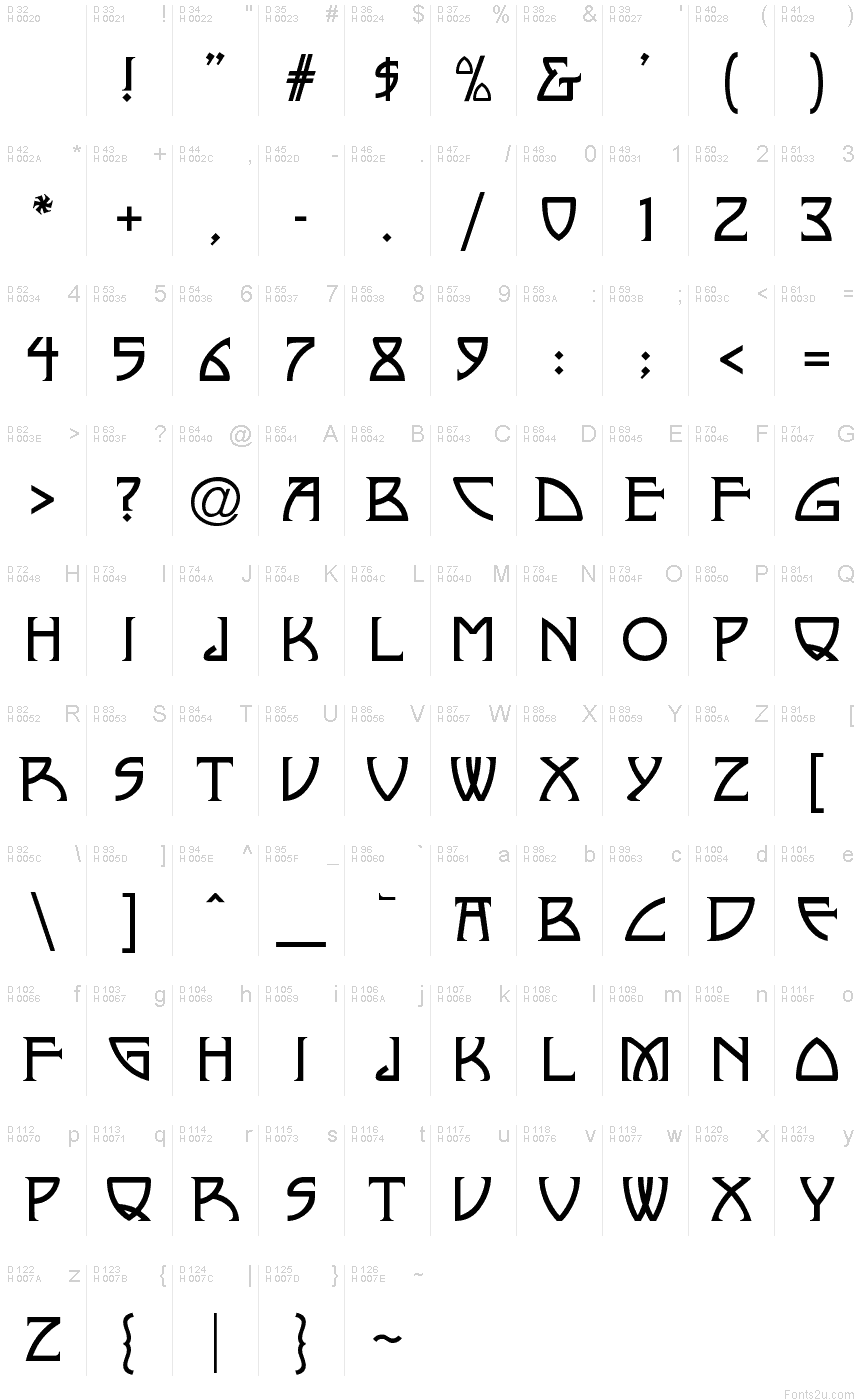
Nickley è il font display retro gratuito di Nick Curtis, con maiuscole che richiamano l'atmosfera dei poster Art Nouveau. L'alternanza di verticali slanciate, curve ampie e avvolgenti e piccoli dettagli affilati rende questo alfabeto elegante e leggermente eccentrico, evitando ogni rigidità formale.
È la scelta naturale per il branding vintage, le copertine dei libri, i menù dei cocktail, i titoli dei film e le brevi testate di riviste dove il ritmo delle lettere gioca un ruolo chiave. Trattandosi di un font gratuito, è perfetto anche per monogrammi e capilettera: le sue curve allungate e i tratti verticali stretti conferiscono a ogni parola una decisa impronta d'altri tempi.